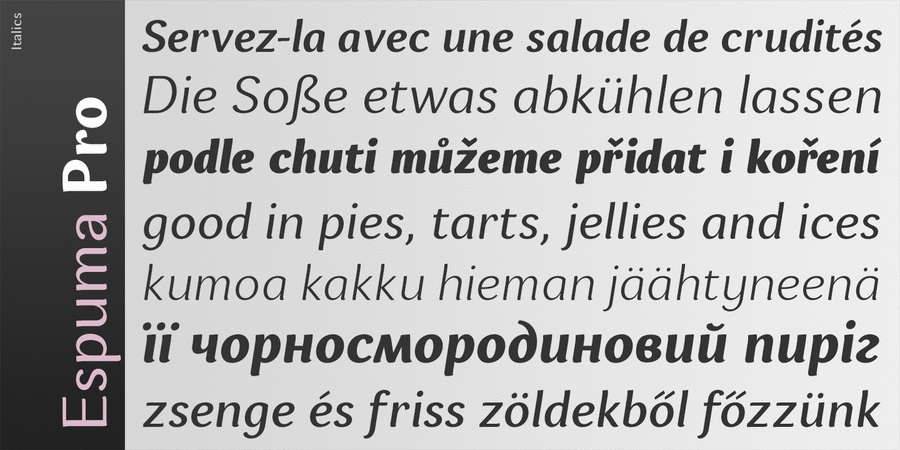
Espuma Pro – м'яка дружня гуманістична гарнітура без зарубок з елементами, що імітують каліграфію браш-пеном. Шрифт має 7 насиченостей та курсивні накреслення, підтримує безліч мов на латинці та кирилиці, містить капітель, 6 наборів цифр і багато лігатур. Його м'які делікатні форми допоможуть брендам, що передають дружелюбність і відкритість. Espuma Pro особливо підходить для упаковки товарів повсякденного попиту, але може також використовуватися в екранній графіці завдяки відмінній читабельності. Шрифт розробив і випустив Андрій Константинов у студії Mint Type у 2013 році.
Асоціації з сімейством шрифтів Espuma ProОсобистість і характер гарнітури:
делікатний, худий, витончений, чистий, легкий, прохолодний, свіжий, модний, якісний, культурний, добірний, благородний, гармонійний, елітний, дорогий, красивий, елегантний, майстерний, естетичний, художній, знаменитий, оригінальний, комільфо, багатий, сучасний, міський, сексуальний, приємний, затишний, комфортний, доброзичливий, ввічливий, акуратний, гнучкий, ясний, спокійний, природний, натуральний, зручний, мирний, добрий, зрозумілий, тактичний, пластичний, динамічний, жіночний, романтичний, ефектний, яскравий, виразний, М'який, соковитий, літній, сімейний, смачний, гладенький, теплий, апетитний, святковий, впевнений, урочистий, помітний, щільний
прикраса, дизайн, ресторан, парфумерія, дієта, лосьйон, краса, туалетна вода, шампунь, косметика, гігієна, чистота, музика, комільфо, квіти, природа, парфуми, графіка, ілюстрація, йога, здоров'я, преміум, готель, шоколад, опера, АСМР, десерт, цукерки, кава, чай, фарба, їжа, кафе, закуска, сік, виставка, фломастери, булочна, літо, відпочинок, родина, магазин, торгівля, молоко, мафін, кондитерська, солодощі, морозиво, випічка, кондитер, подарунки, свято, сир, обід, вечеря Гарнітура має ознаки стилів:
— Гарнітура асоціюється з віком: